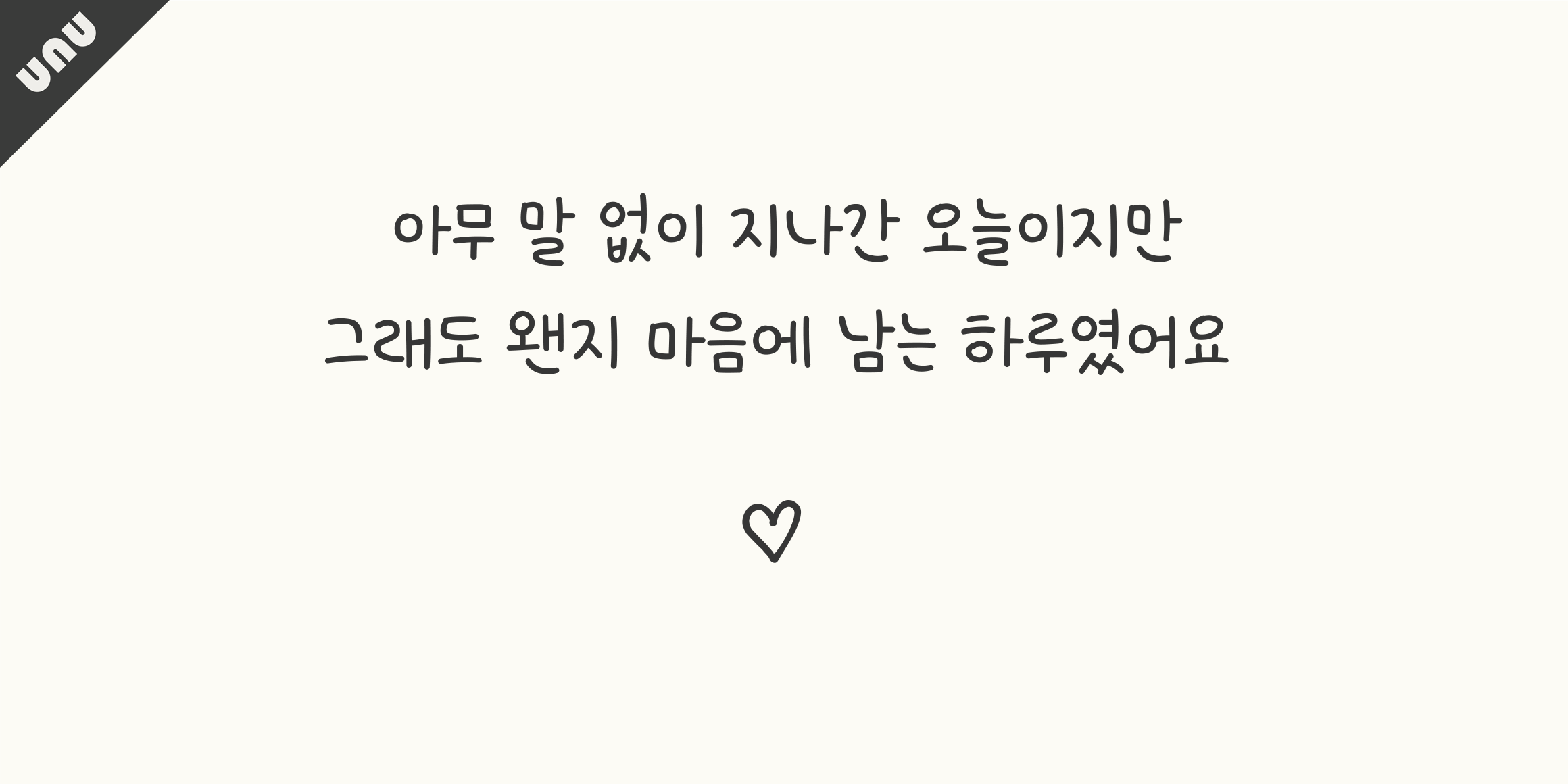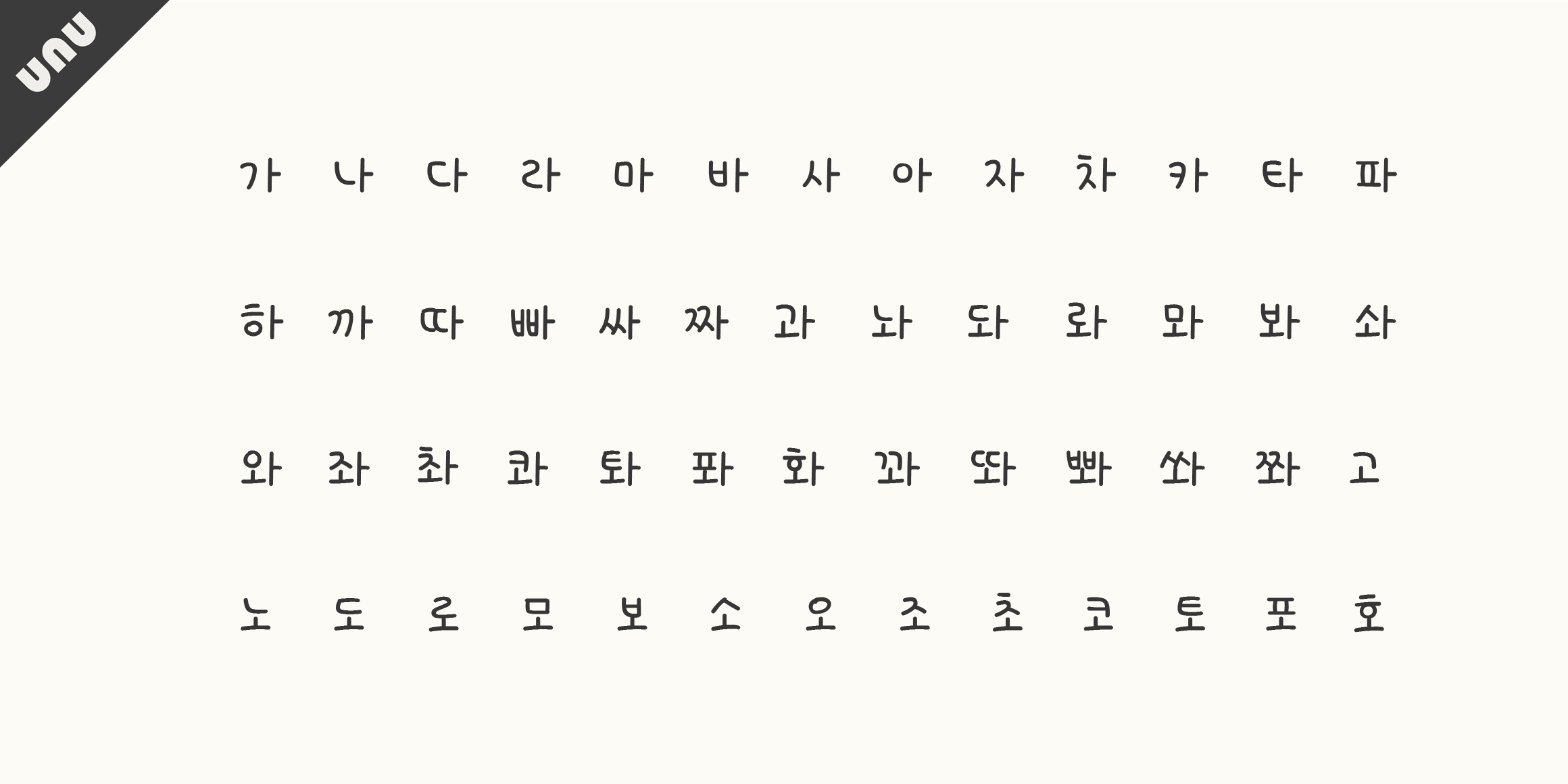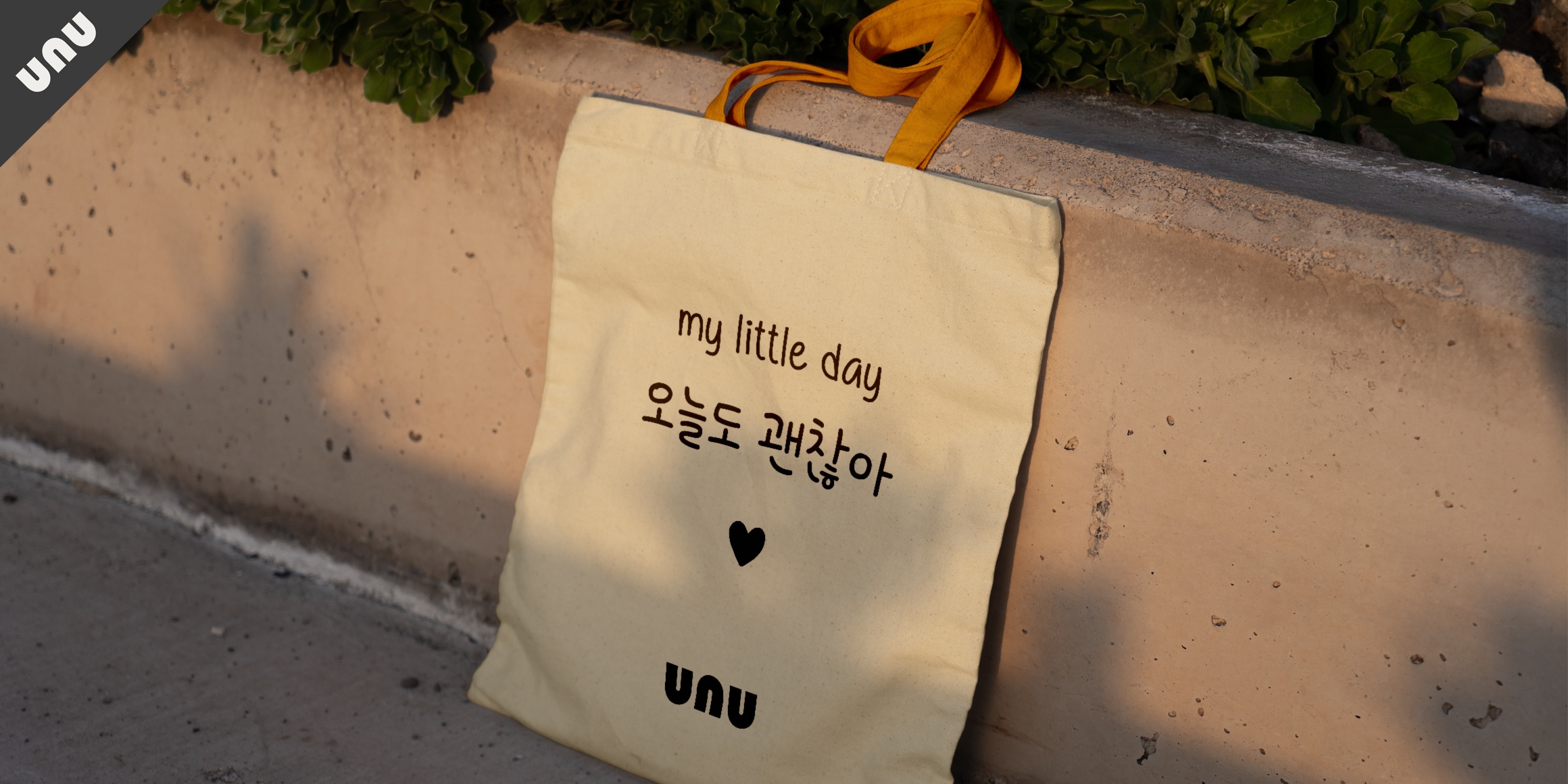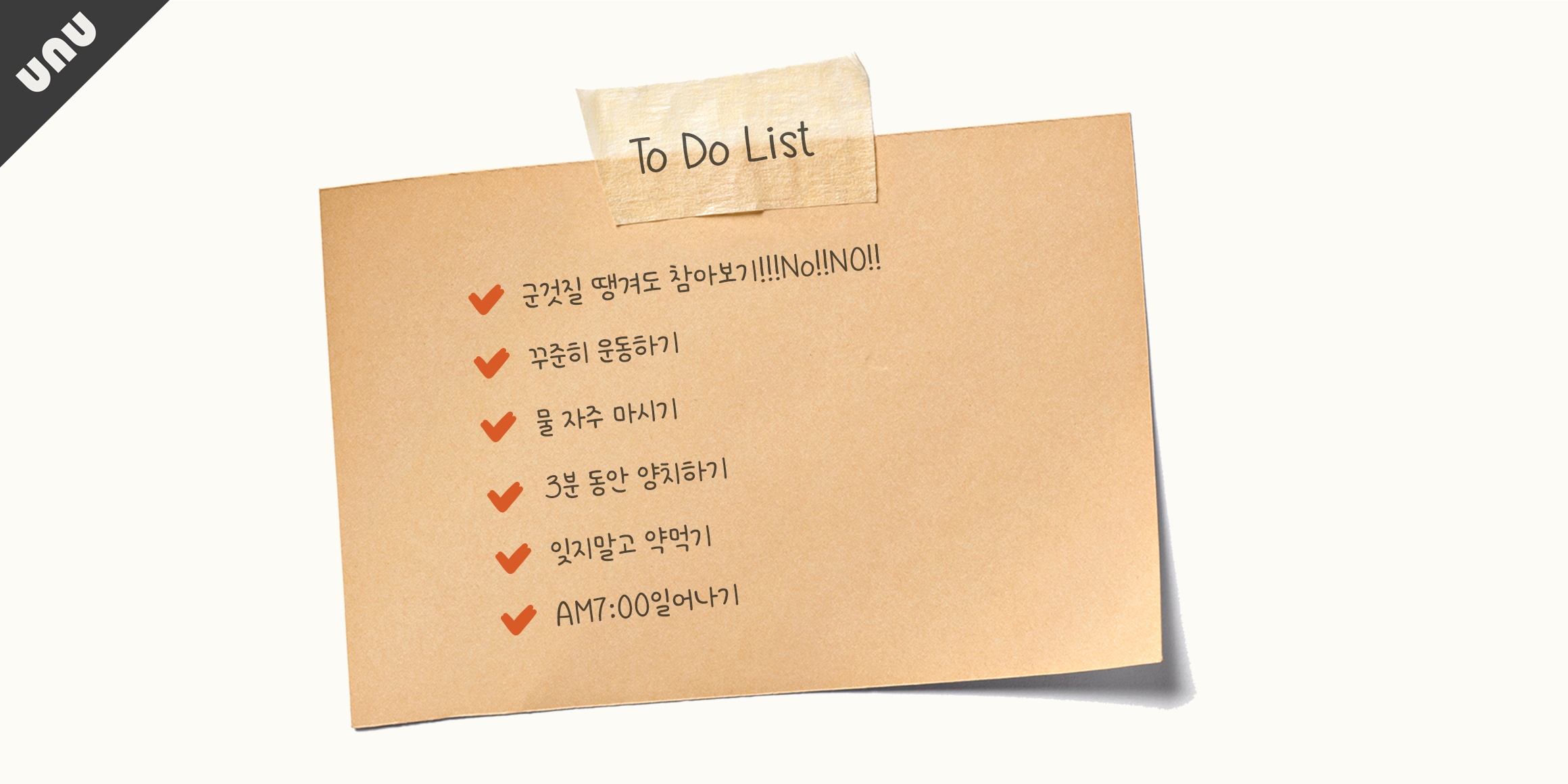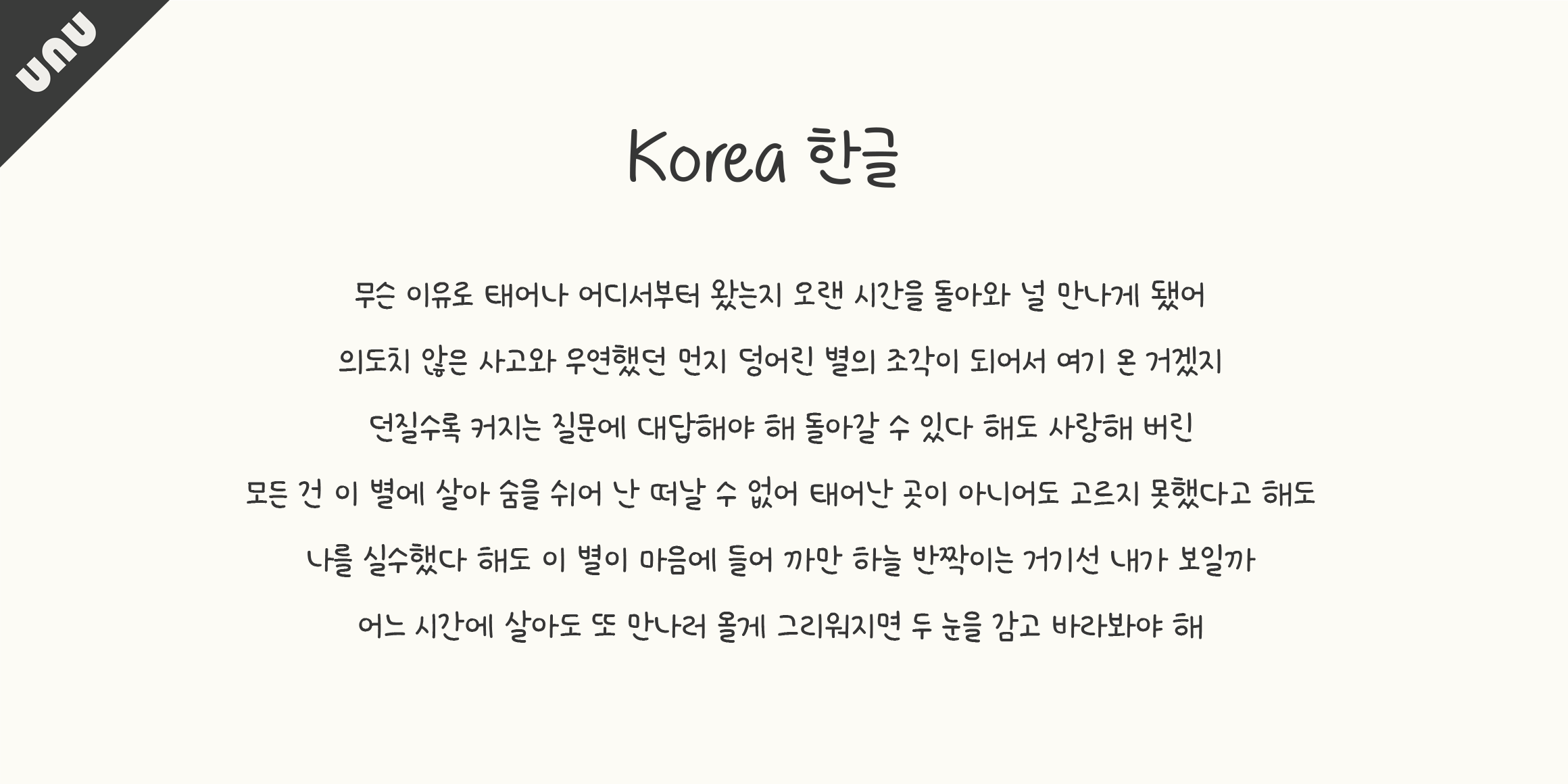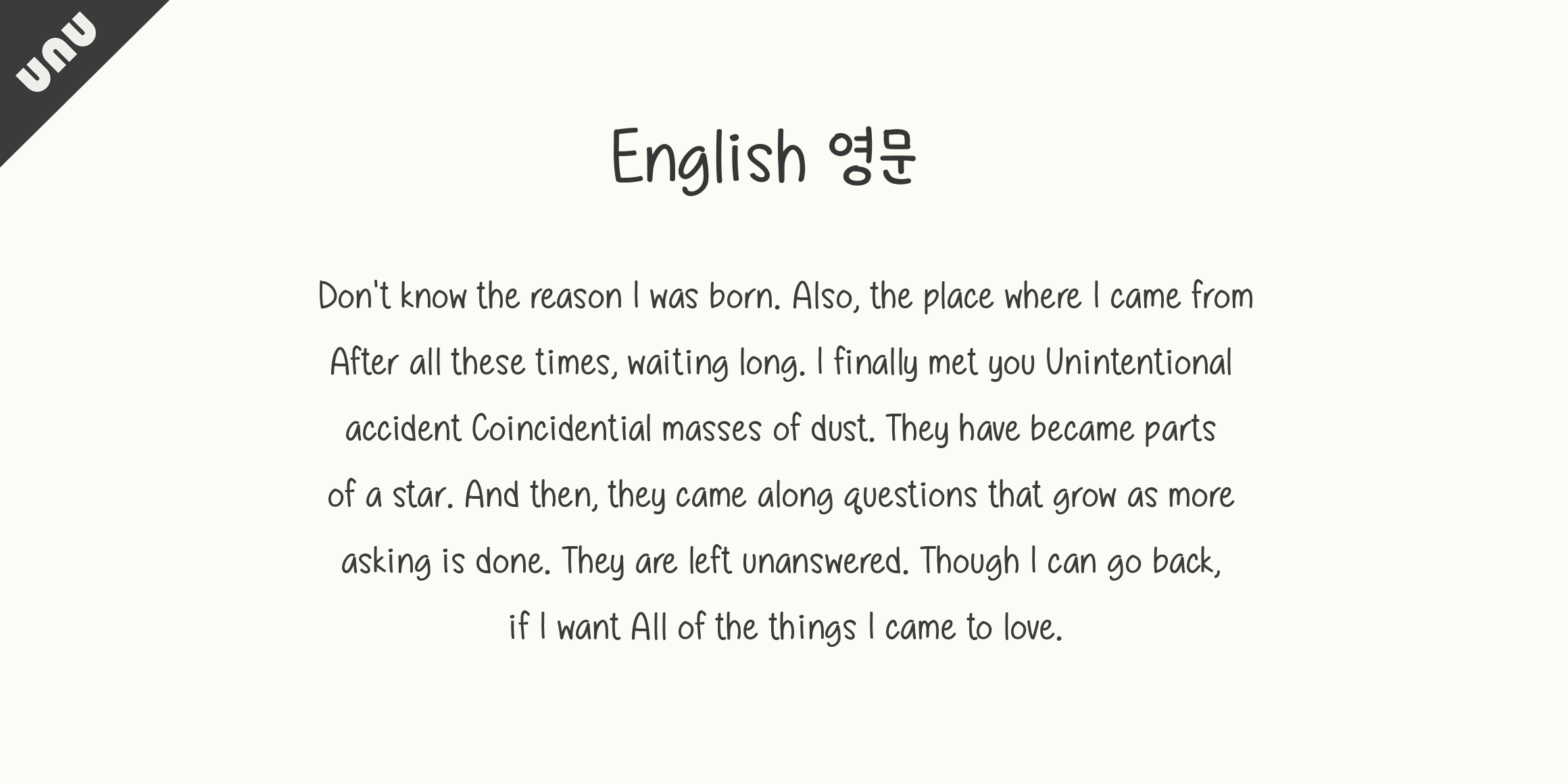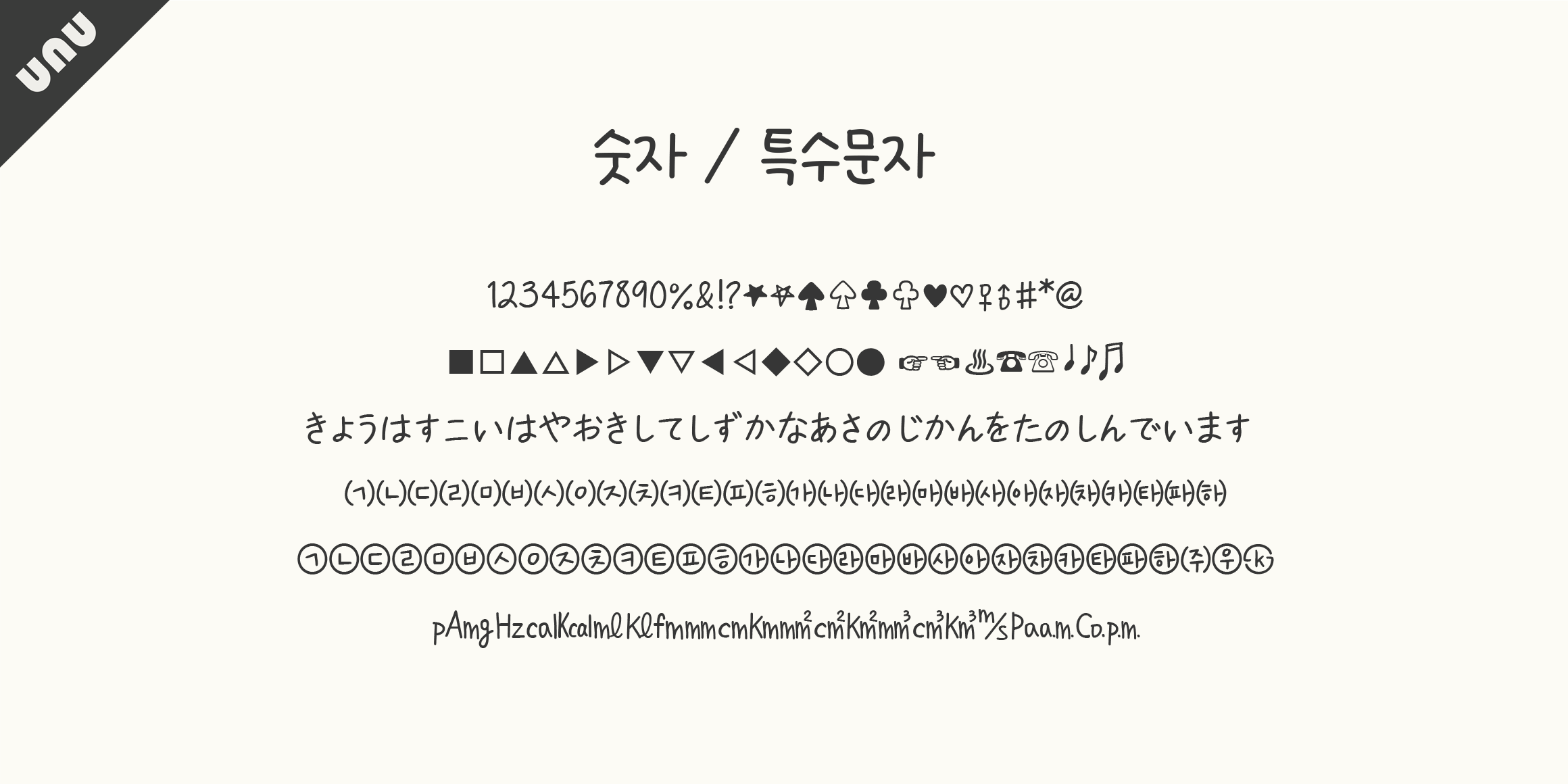
unu 소원을빌어요
unu
분류 Script,손글씨
제목용본문용서정적
unu 소원을빌어요 font in use
이 서체는 친근한 곡선이 자연스럽게 표현된 사랑스러운 손글씨입니다. 사랑하는 누군가에게 따뜻한 마음을 전하고 싶을때, 내 소중한 다이어리에 오늘을 기록하고 싶을때 추천드립니다. 유앤유서체는 당신의 따뜻한 마음을 전해드립니다.
• Script,손글씨
• unu 소원을빌어요 / unu Makeawish